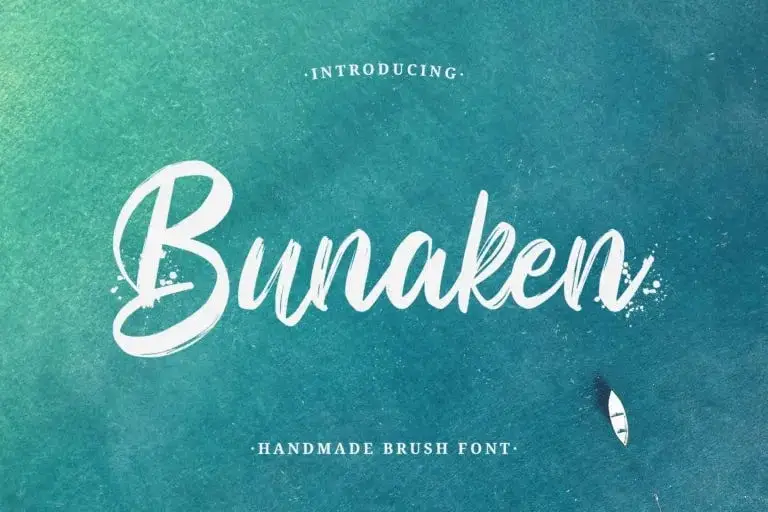
Bunaken Brush Font – Fonte Grátis
Bunaken Brush Font
Bunaken Brush Font é mais do que outra tipografia de letra esfregada manualmente. Embala a essência contemporânea e elegância ao mesmo tempo. Desenhado e compartilhado pela Typefactory, Bunaken exibe uma presença assertiva, mas sofisticada. Suas letras grossas e extensas são perfeitas para logos, marca identidade visual e design de embalagens, entre outras aplicações. É um script grafita que se tornou uma verdadeira necessidade na sua coleção. Seja em qualquer projeto de design, Bunaken trará um toque elegante à sua tipografia.